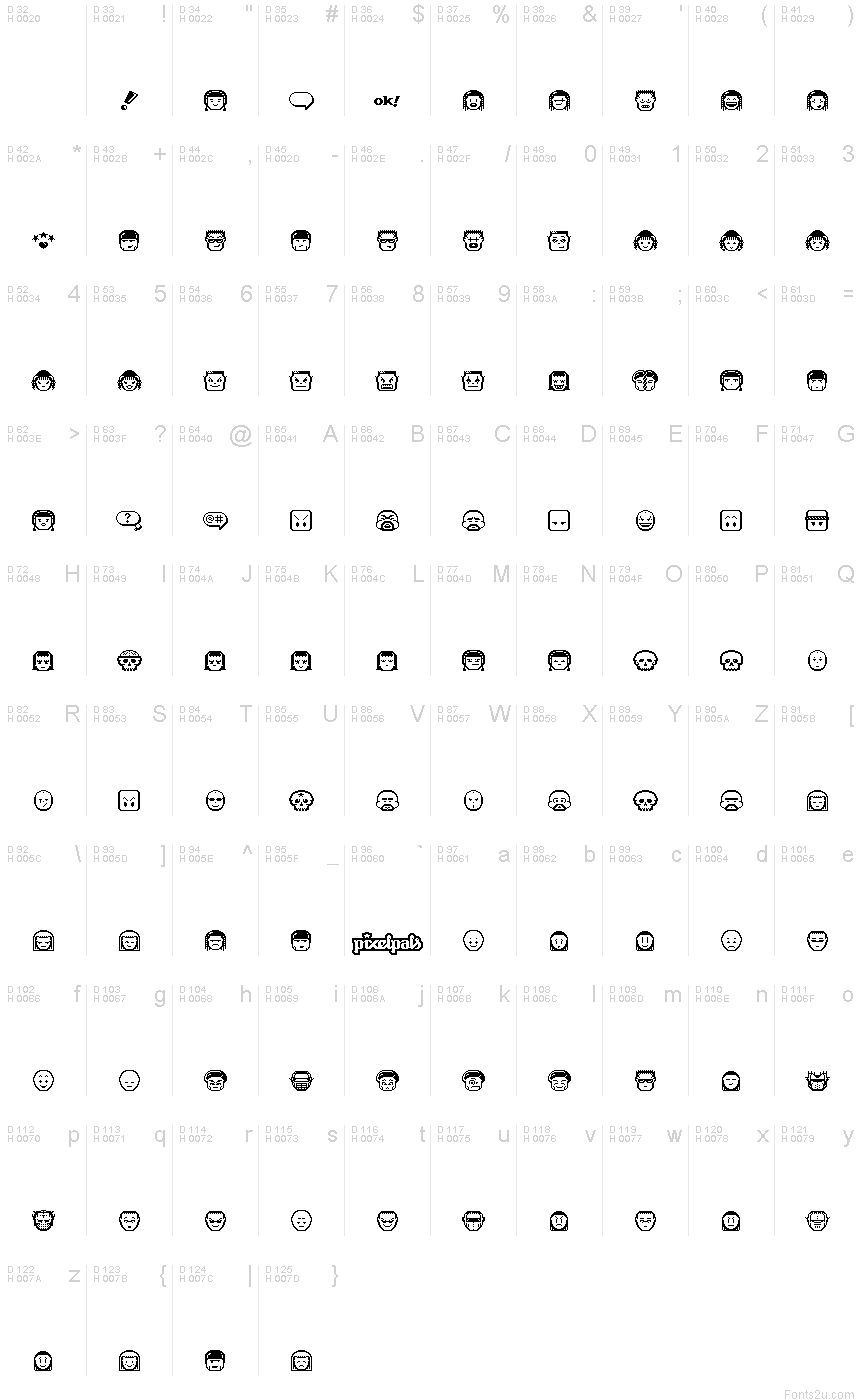
V5 Pixelpals Tipo de letra
V5 Pixelpals, de Roberto Christen da vFive, é uma fonte pixel art gratuita construída com base em rostos humanos marcantes. O conjunto tem o charme dos primeiros ecrãs digitais: arestas quadradas, contornos em bloco e expressões simples repetem-se ao longo dos caracteres, enquanto os diferentes penteados, máscaras e formatos de cabeça mantêm o ambiente lúdico, longe de parecer apenas um conjunto de ícones.
Esta fonte gratuita faz sentido onde quer que pretenda imprimir humanidade e personalidade numa pequena voz digital — títulos de zines, menus de jogos, autocolantes, cartazes com temática de chat ou títulos de álbuns de recortes. Funciona também muito bem em etiquetas curtas, emblemas e pequenos elementos gráficos, onde estes rostos compactos atuam como pequenas personagens em vez de simples ornamentos.